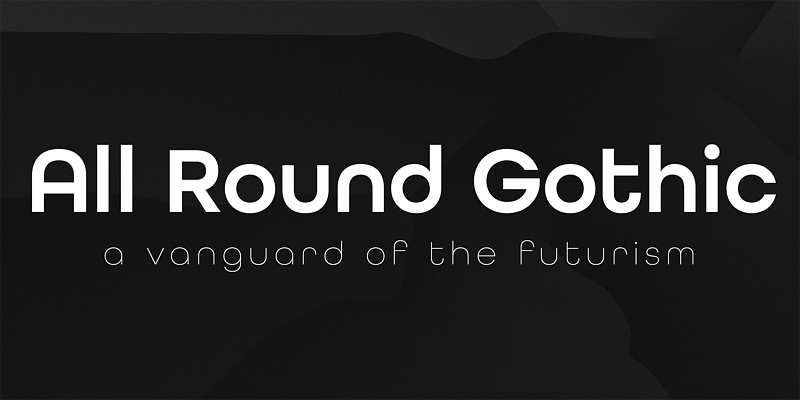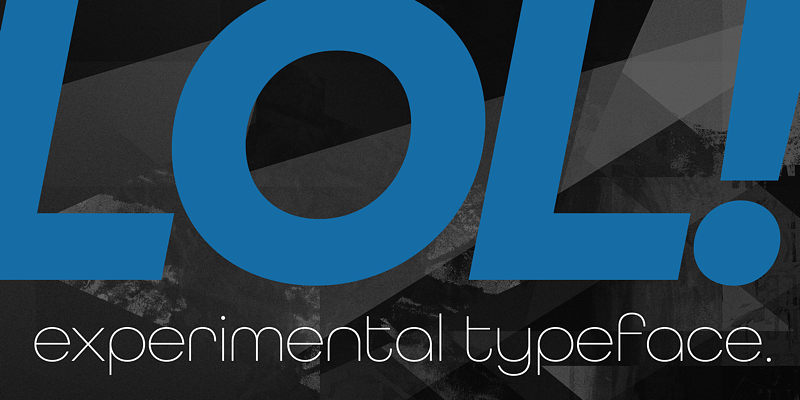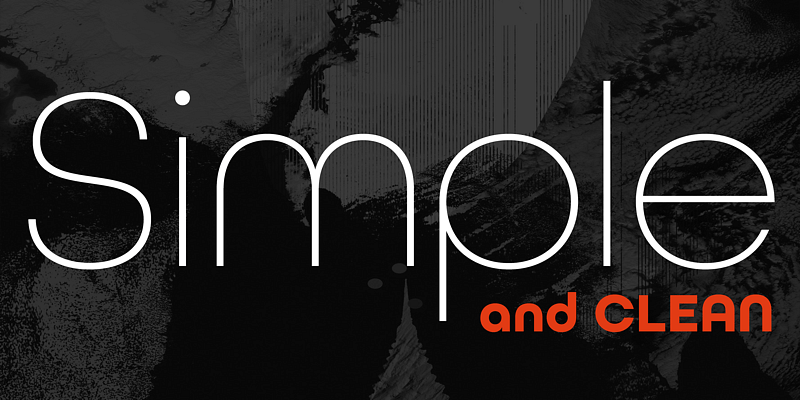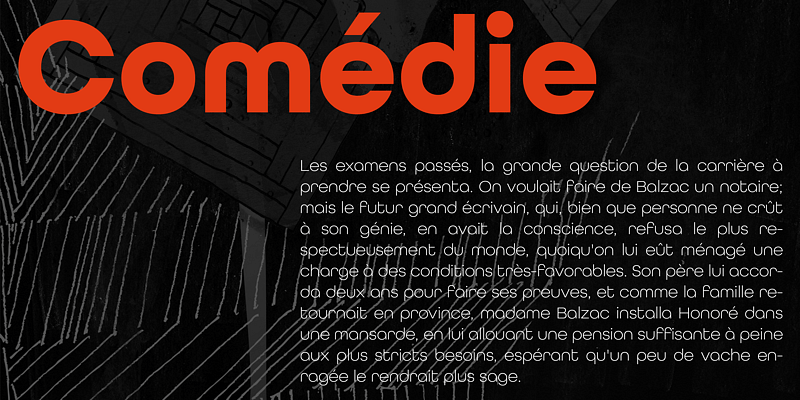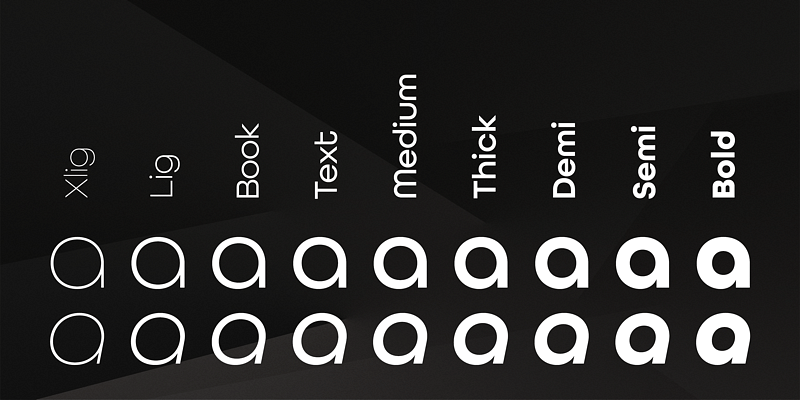
All Round Gothic ist eine Schriftfamilie, die von klassischen serifenlosen Schriftarten inspiriert ist. Diese Schriftart ist eine strukturierte geometrische Sans, schafft aber auch durch den Verzicht auf unnötige Stämme eine süße und niedliche Atmosphäre.